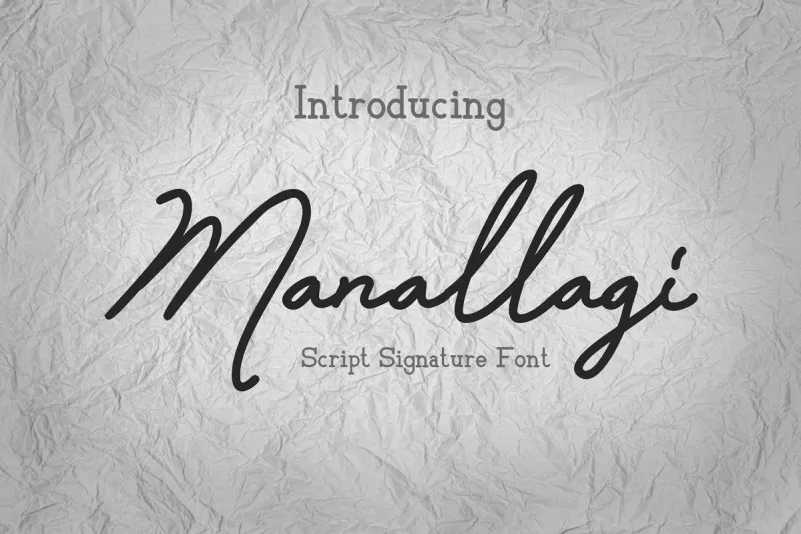
A Manallagi Script é uma fonte de traços que traz beleza e naturalidade a qualquer projeto. Se você está procurando por um traço para sua assinatura, já encontrou! Essa nova font se destaca por seu estilo handwritten e script moderno e fresco. Ela consegue ser elegante e perfeitamente adaptável a projetos que exigem o sabor do traçado manual. Não espere mais: com Manallagi Script, você pode adicionar um toque único de autenticidade aos seus trabalhos. Este design da M.0Type é ideal para aqueles projetos onde a mão não tem precedente.